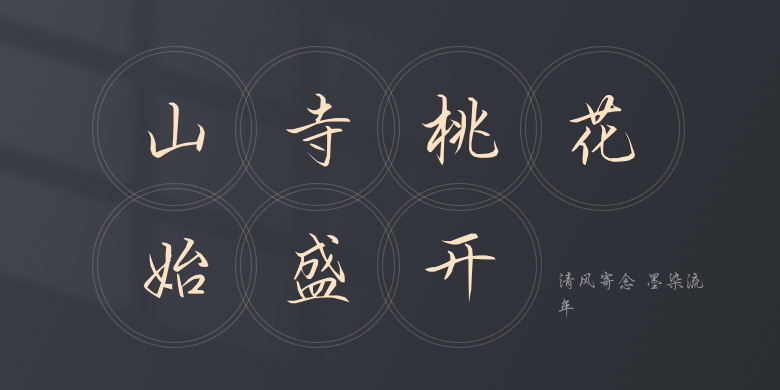
清风寄念 墨染流年
清风寄念 墨染流年,这款字体结构工整、笔画清晰,兼顾美观与易读性,适用于标题、正文、海报、包装、LOGO 等多种场景。字形优雅稳定,风格百搭耐看,适配日常排版与创意设计,让文字呈现更舒适、更具质感。清风寄念 墨染流年一笔一画,皆是细节,以均衡的比例、流畅的线条打造舒适视觉体验,字形端正大气,风格简约现代。无论是商业设计、品牌宣传还是日常排版,都能轻松驾驭,让文字更有格调与力量。清风寄念 墨染流年字体下载。